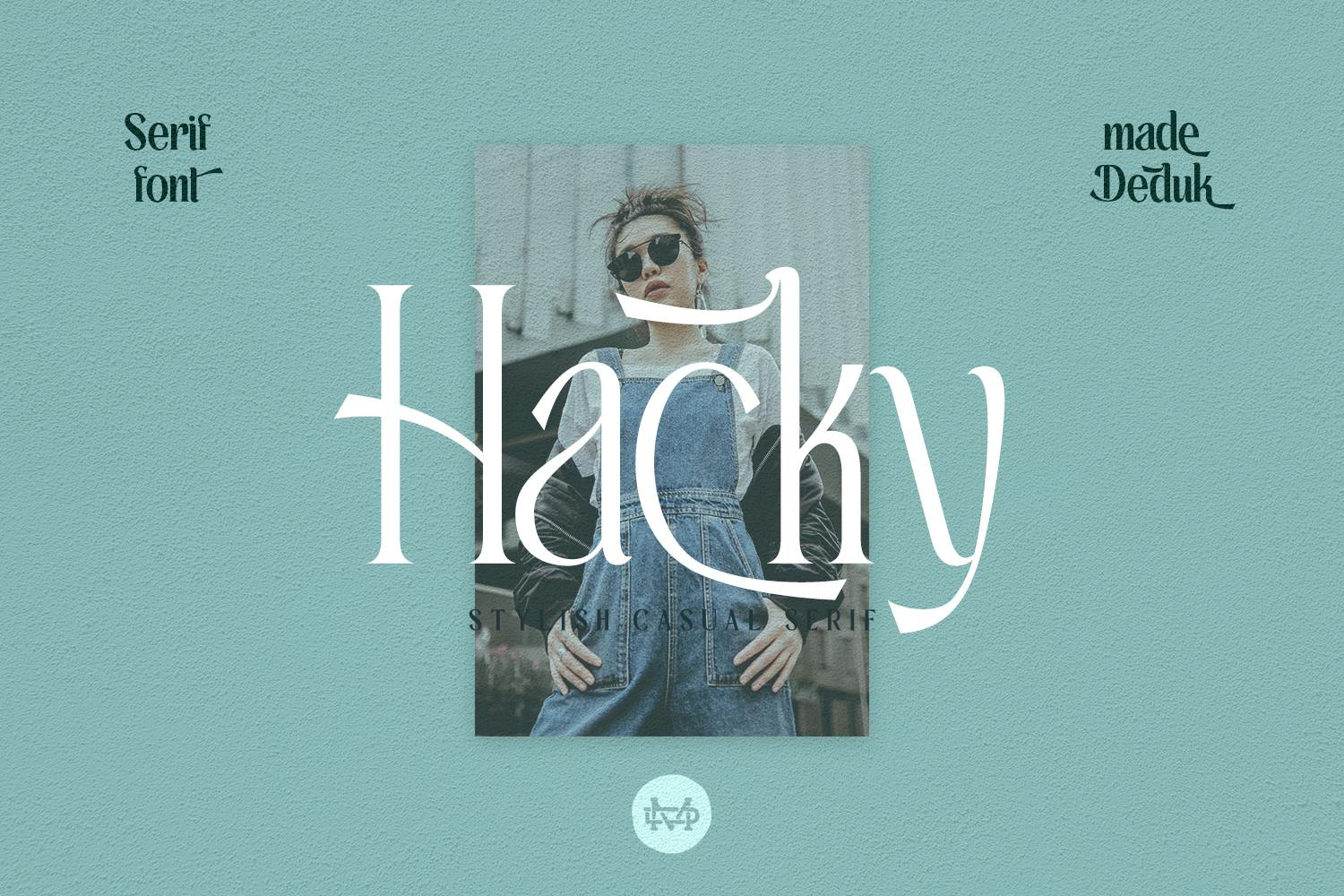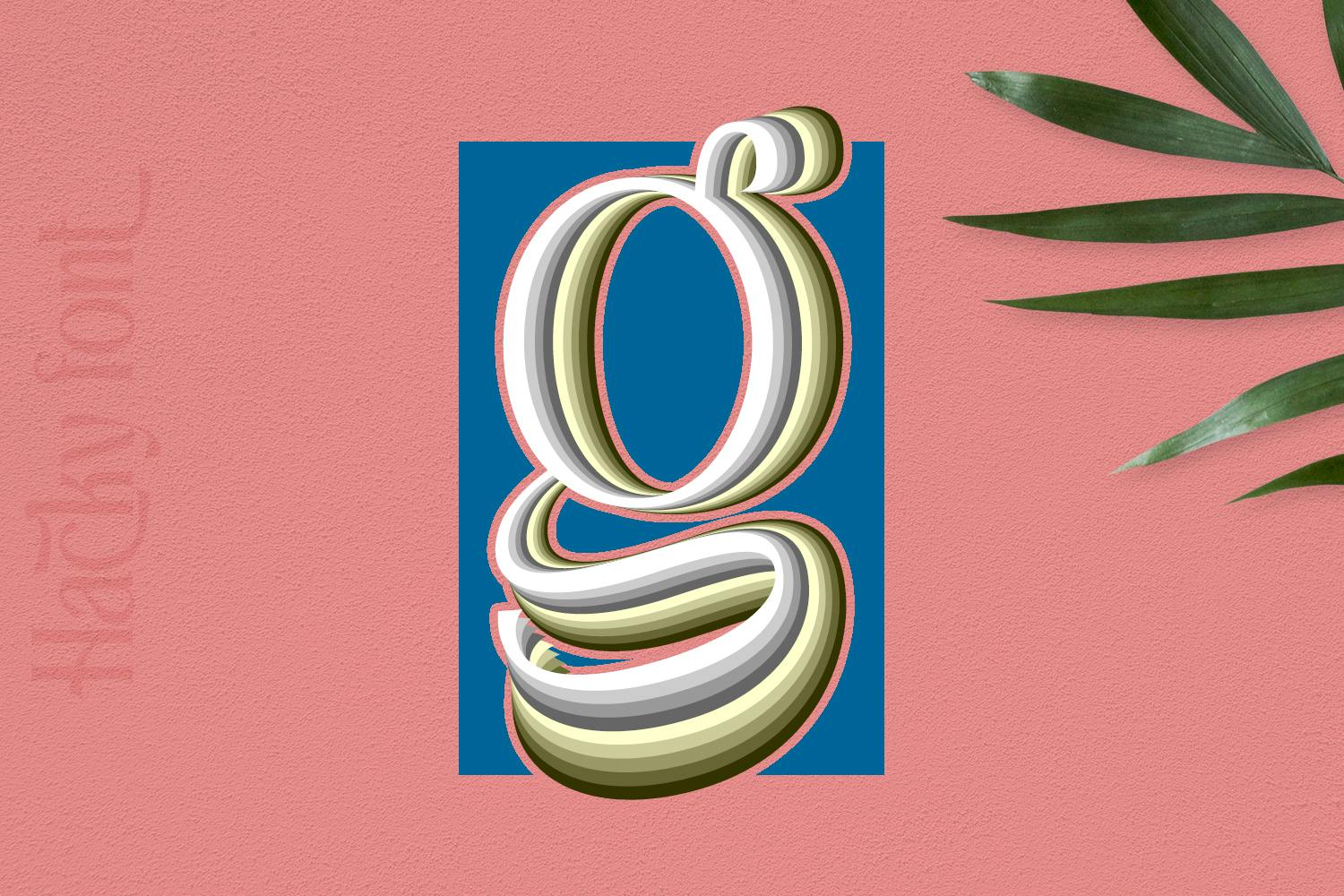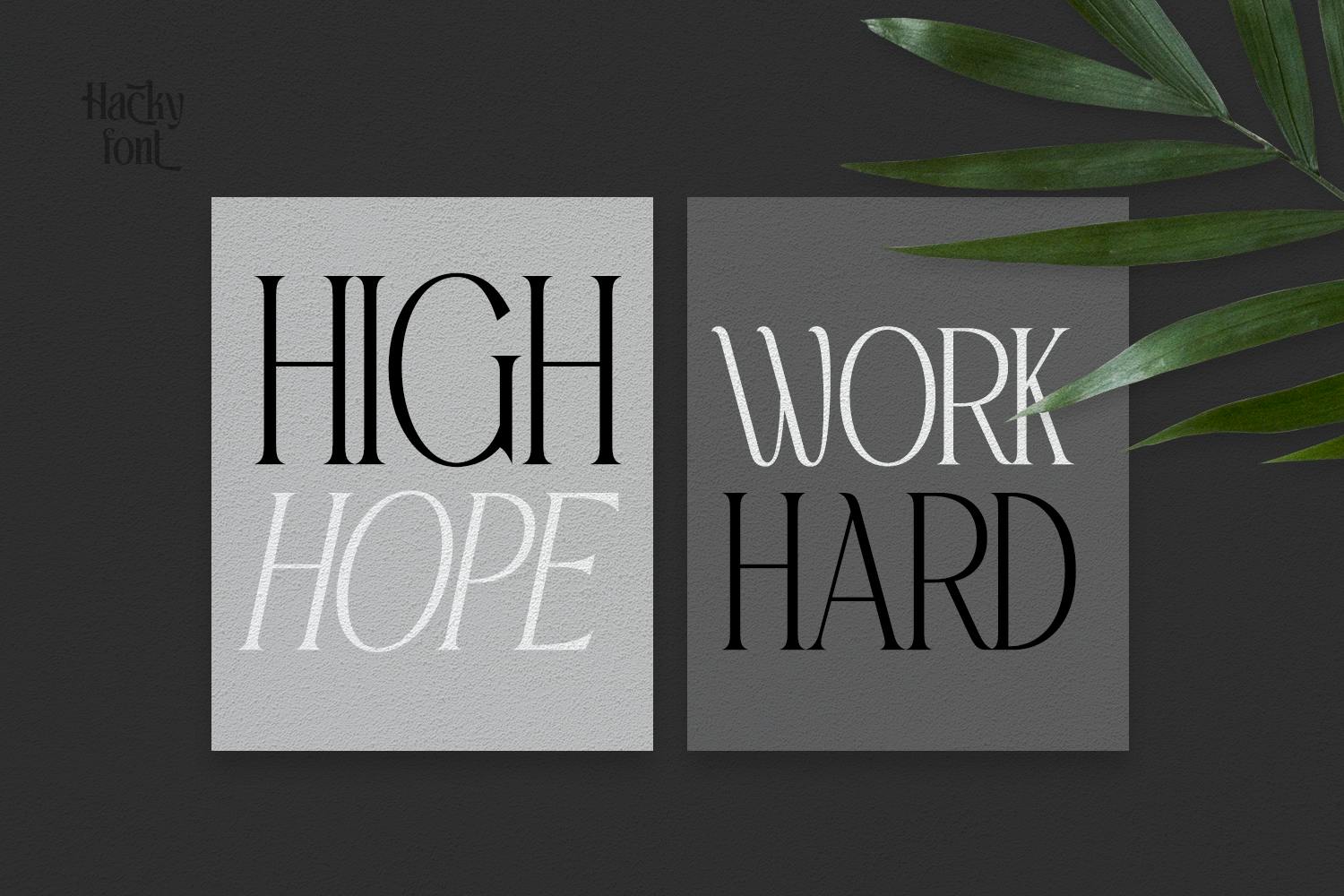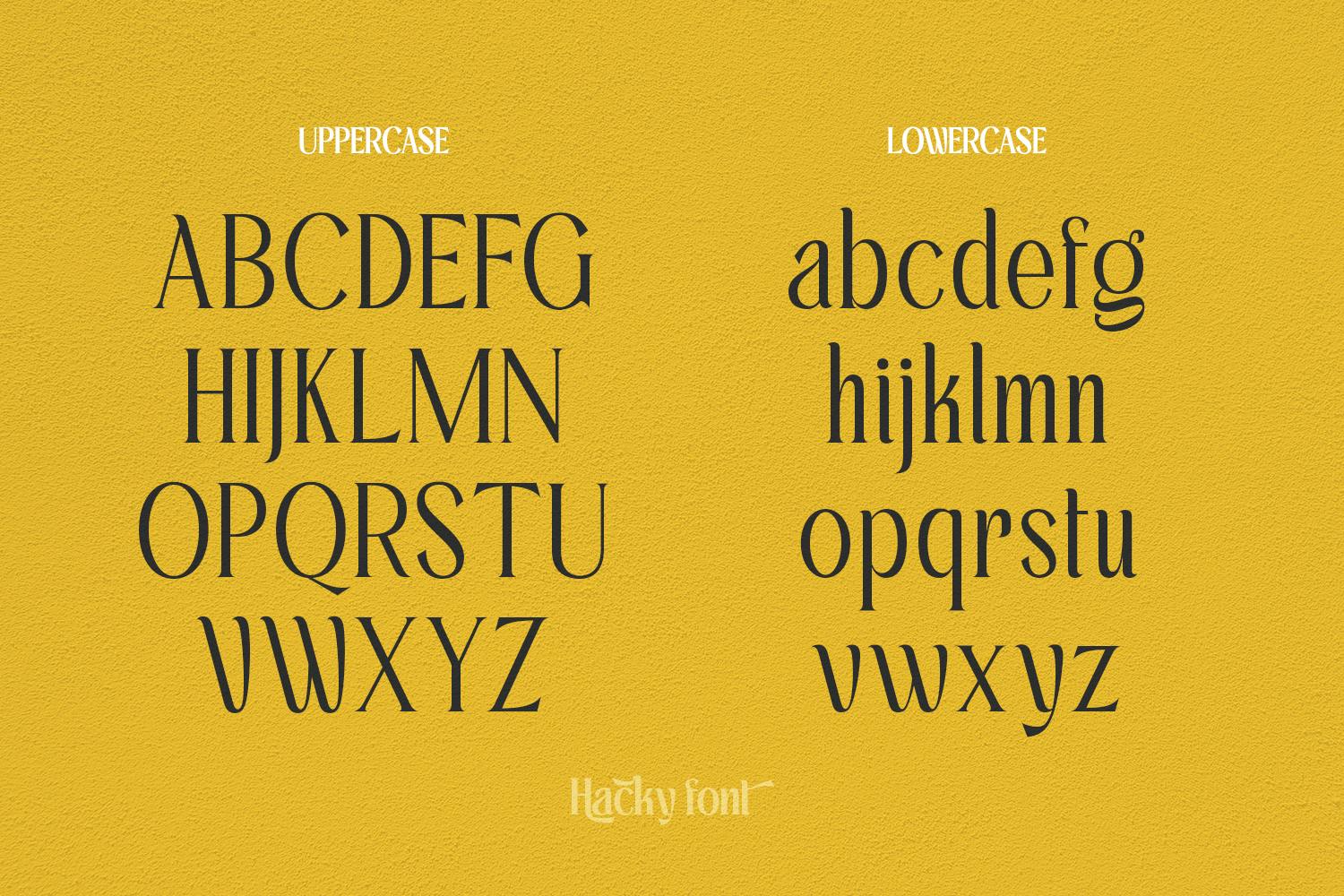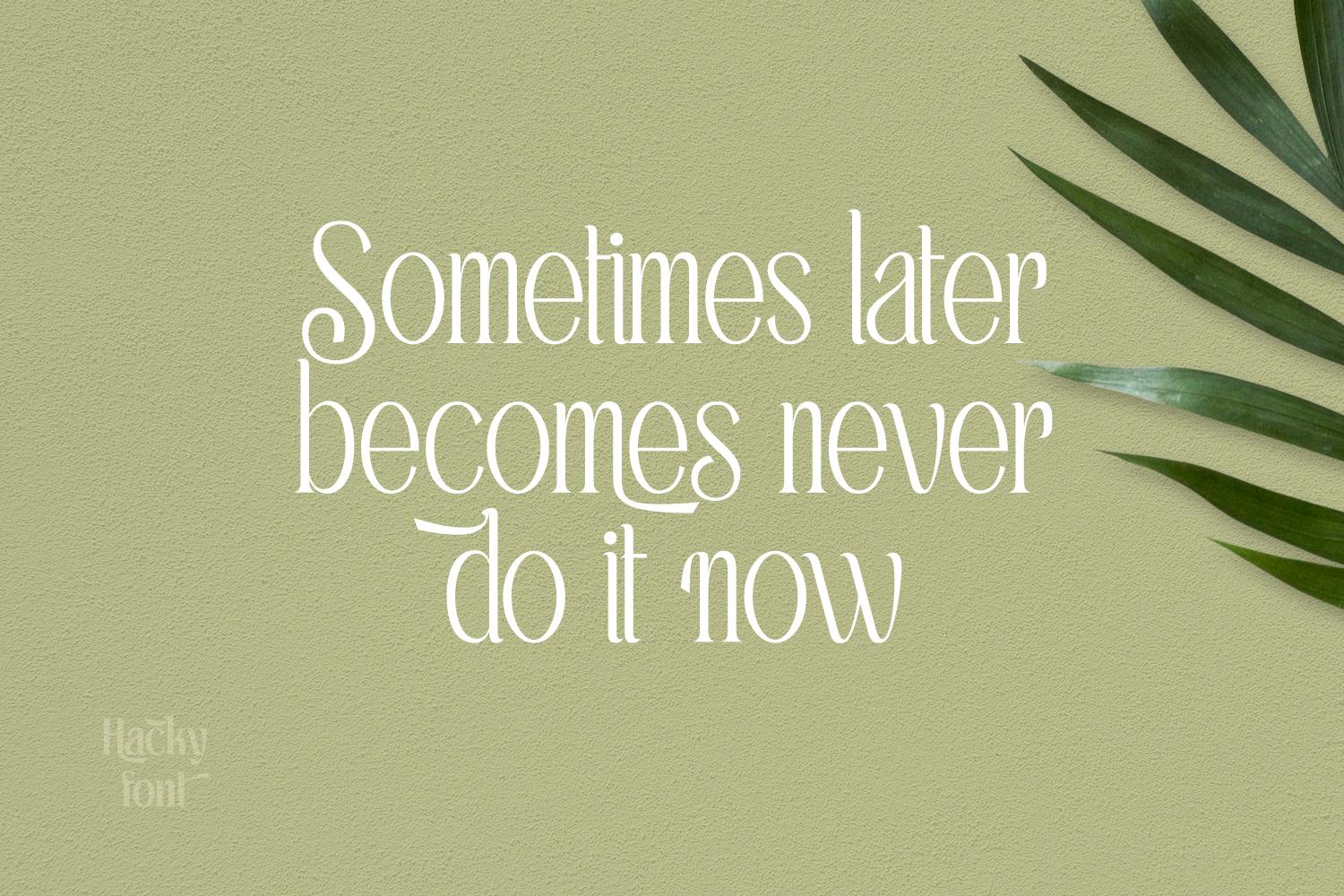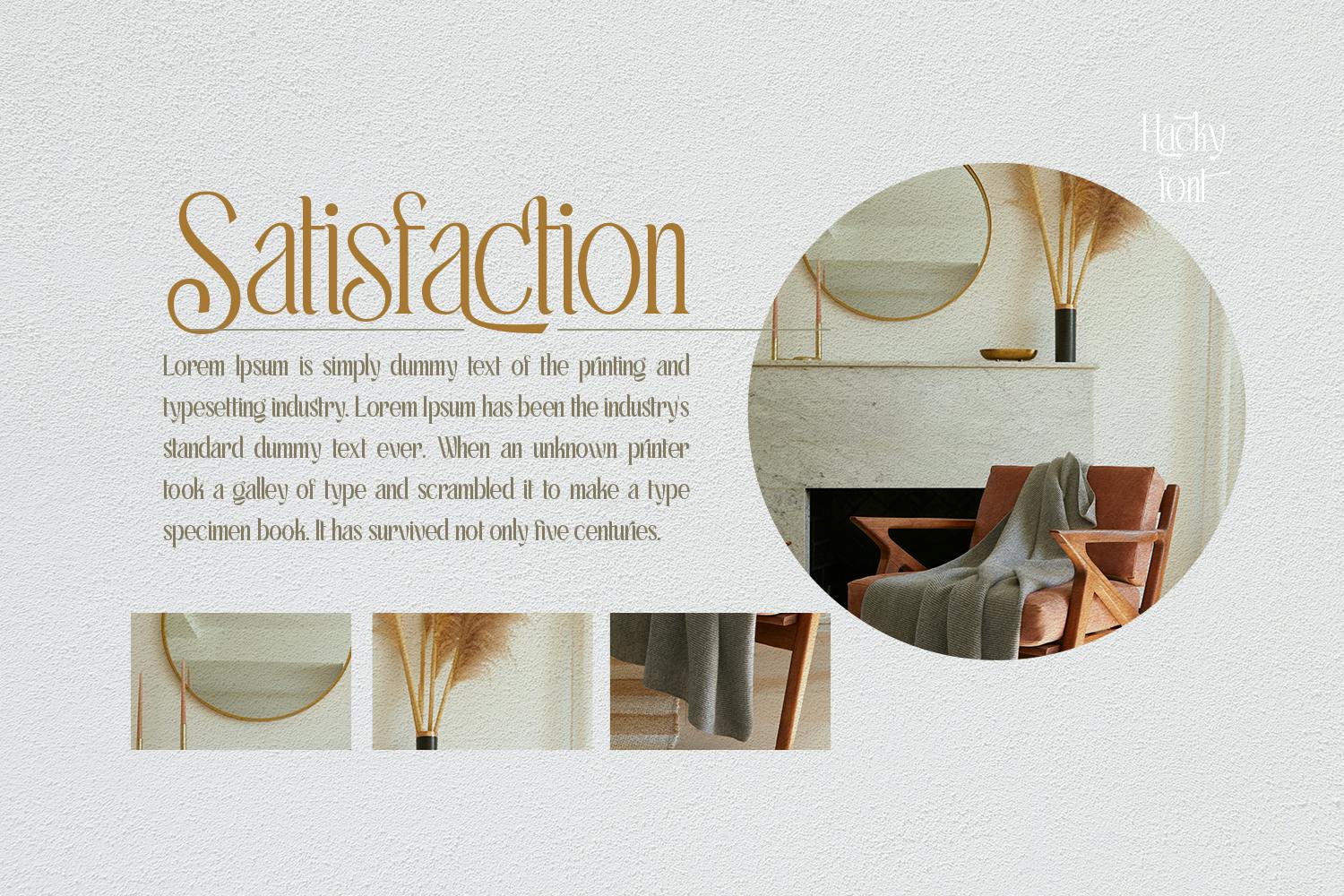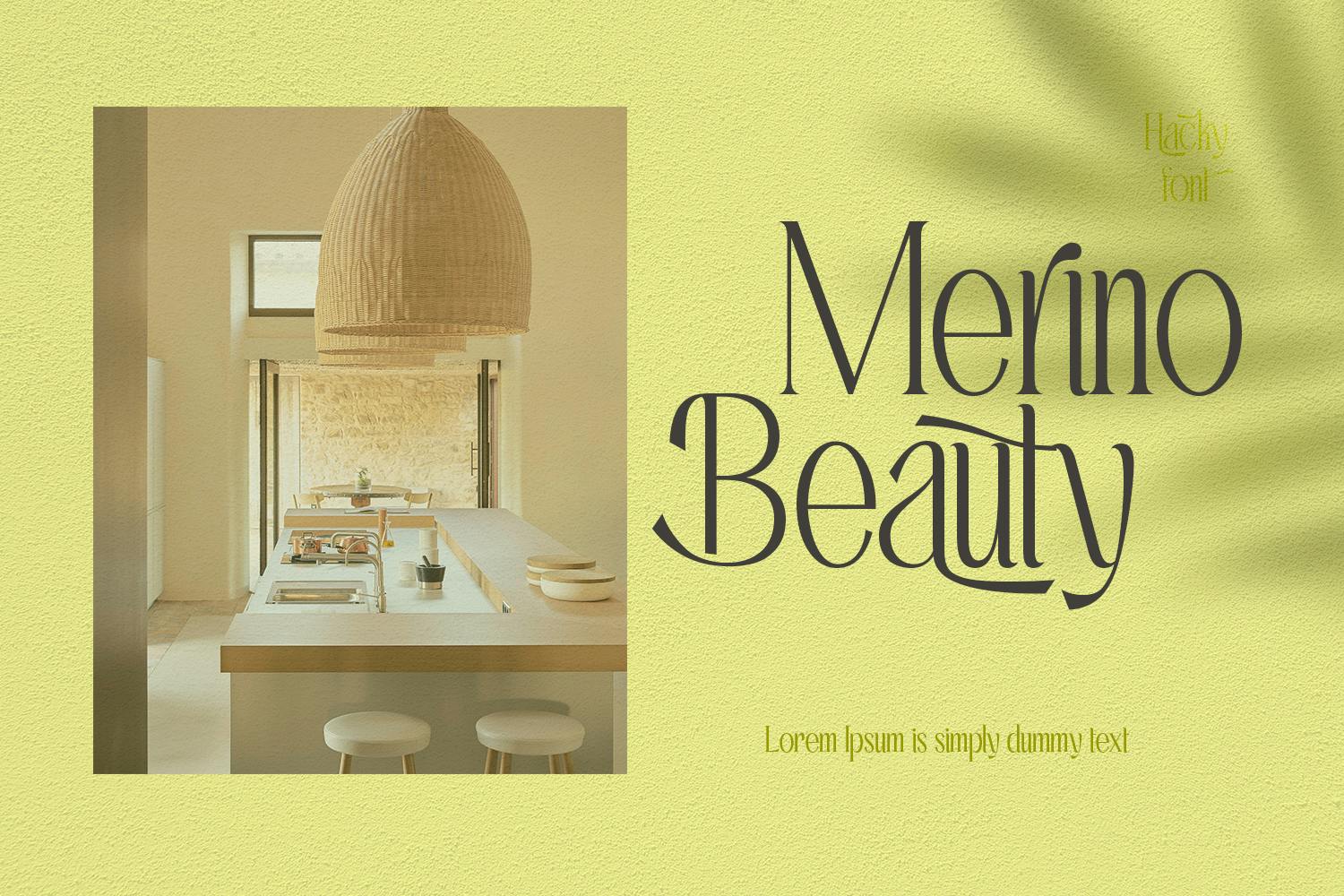
Hacky Luxury Serif Font
فونت Hacky با طراحی لوکس و زیبا، مناسب برای پروژه‌های مختلف.
فونت Hacky یک فونت سریف لوکس و شیک است. این فونت با طراحی تمیز و زاویه‌های نرم خود، شامل گزینه‌های متنوعی برای استفاده در پروژه‌ها می‌باشد. این فونت مناسب برای ایجاد هر نوع برندسازی، بسته‌بندی محصولات، دعوت‌نامه‌ها، نقل قول‌ها، تی‌شرت‌ها، برچسب‌ها، پوسترها و لوگوها است.
ویژگی‌ها
• حروف بزرگ (UPPERCASE)
• حروف کوچک (Lowercase)
• اعداد و نمادها
• گلیف‌های بین‌المللی
• گزینه‌های جایگزین
• لیگچرها